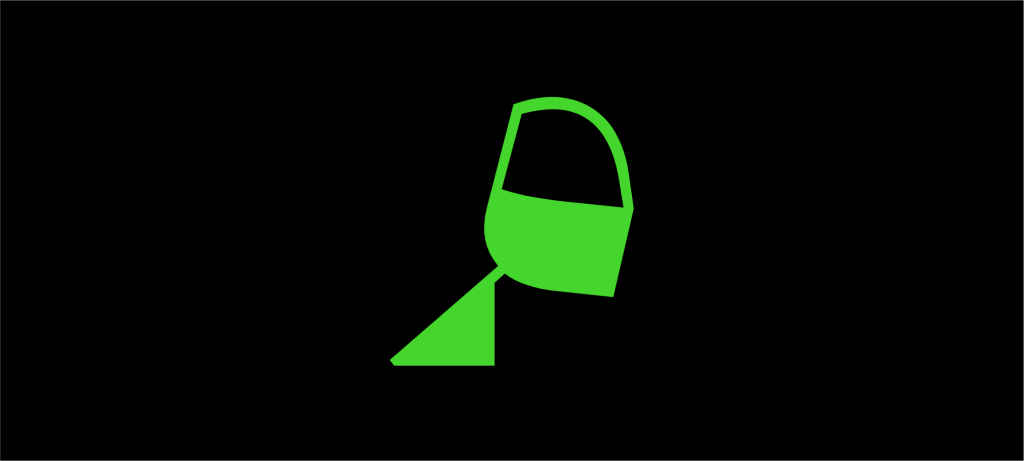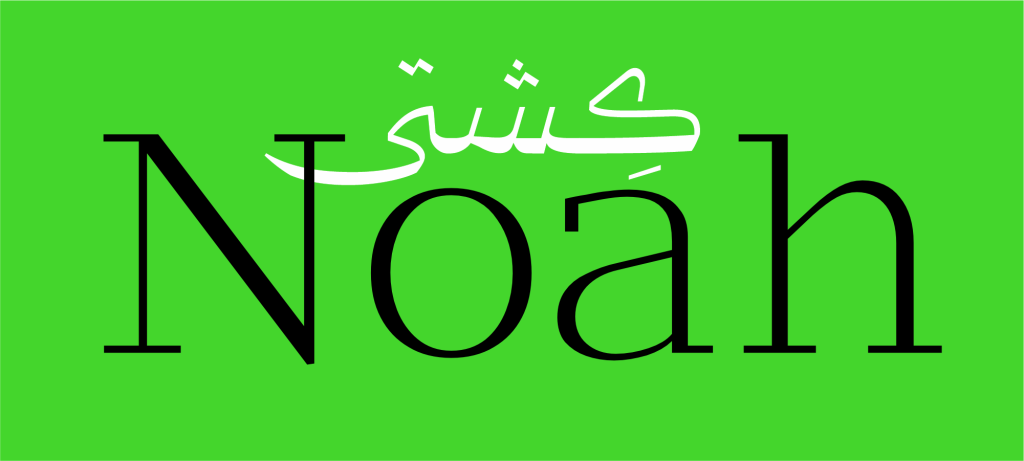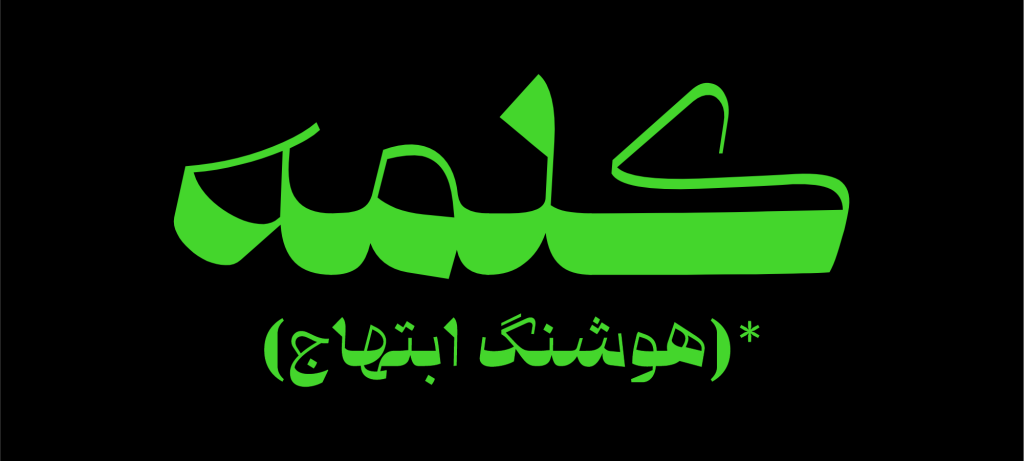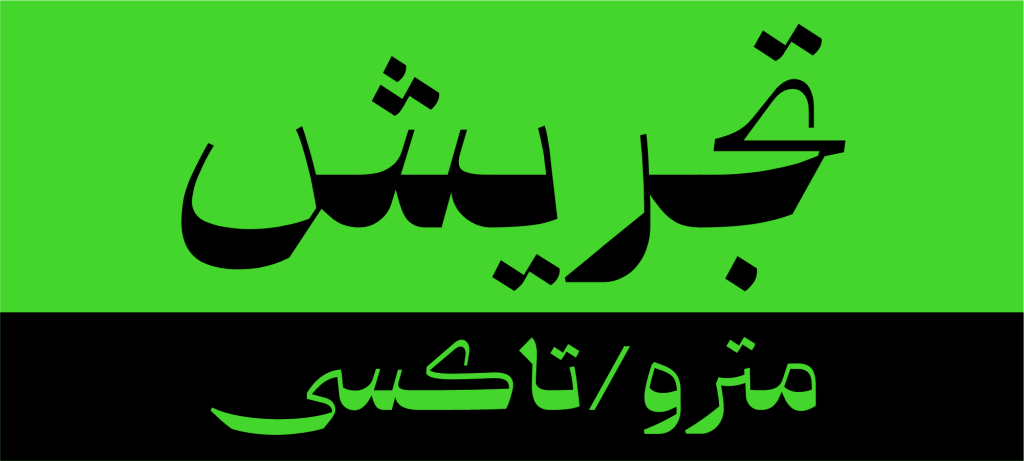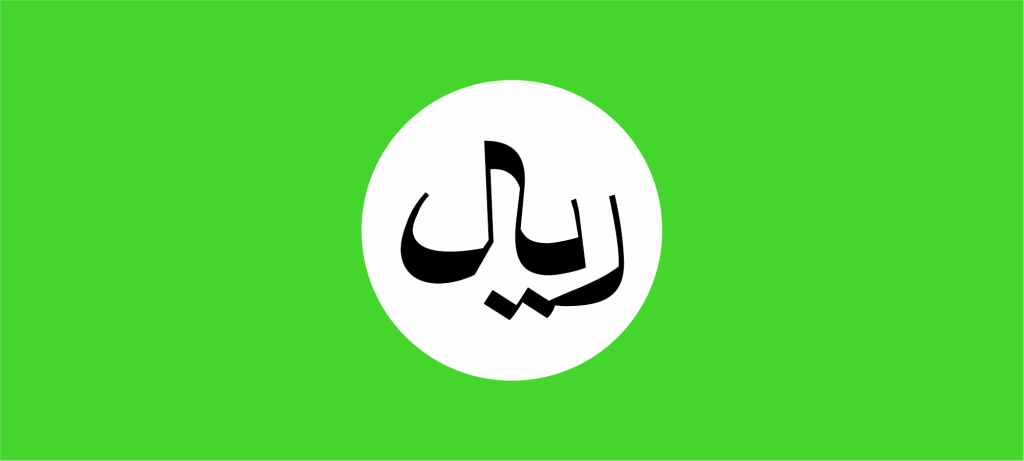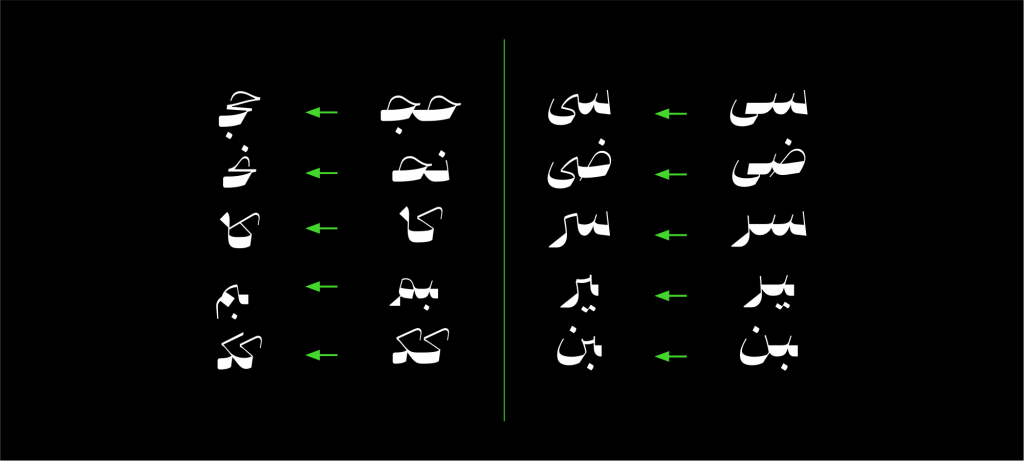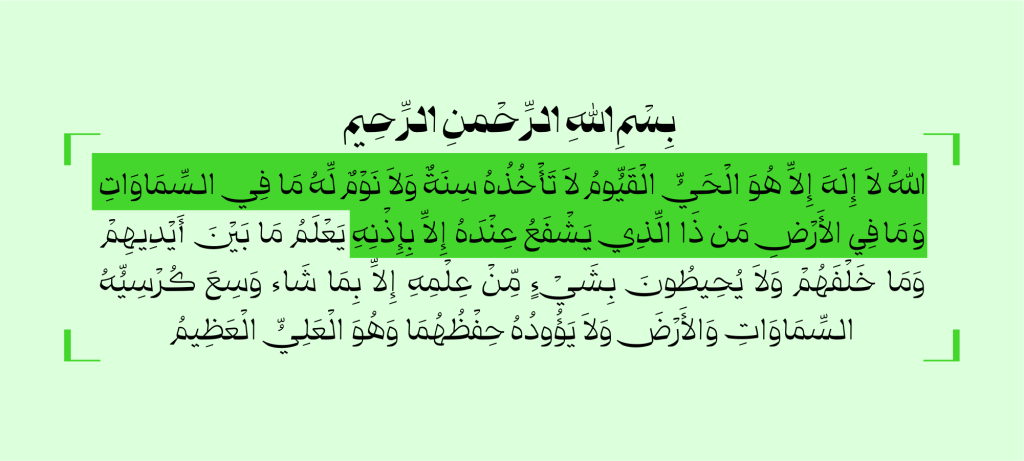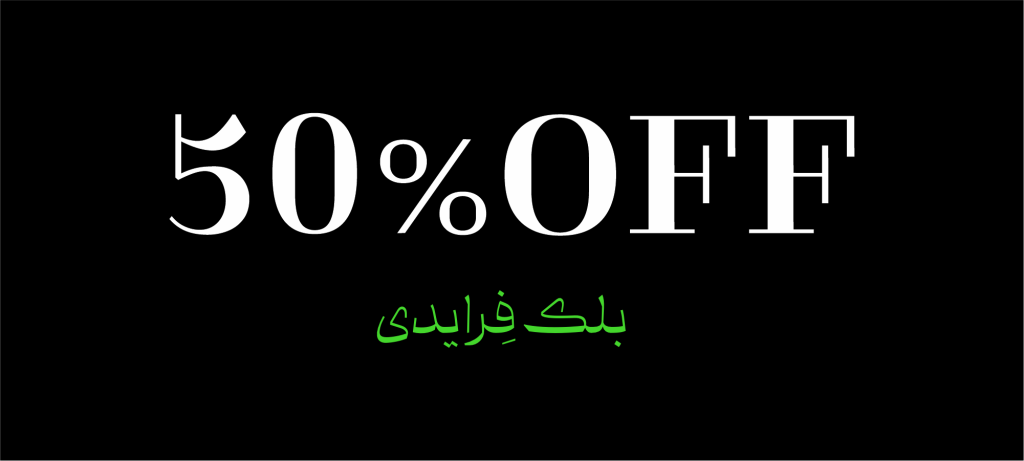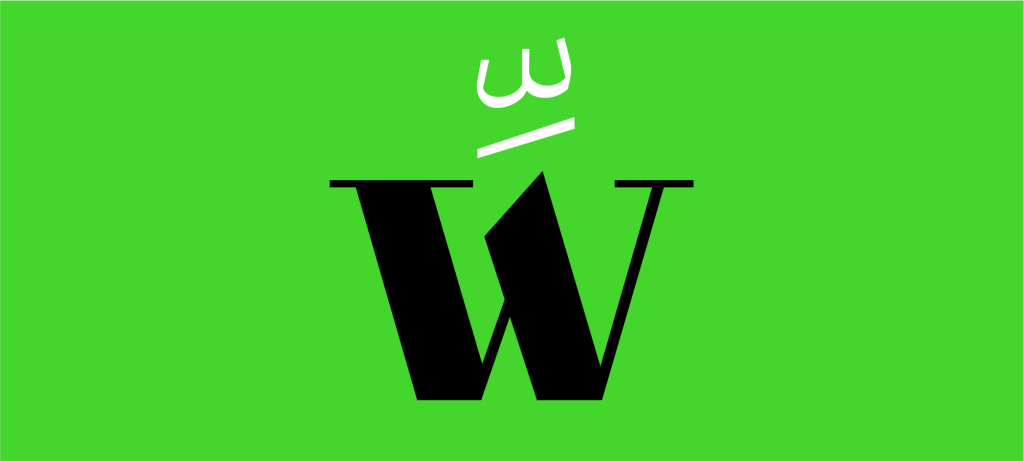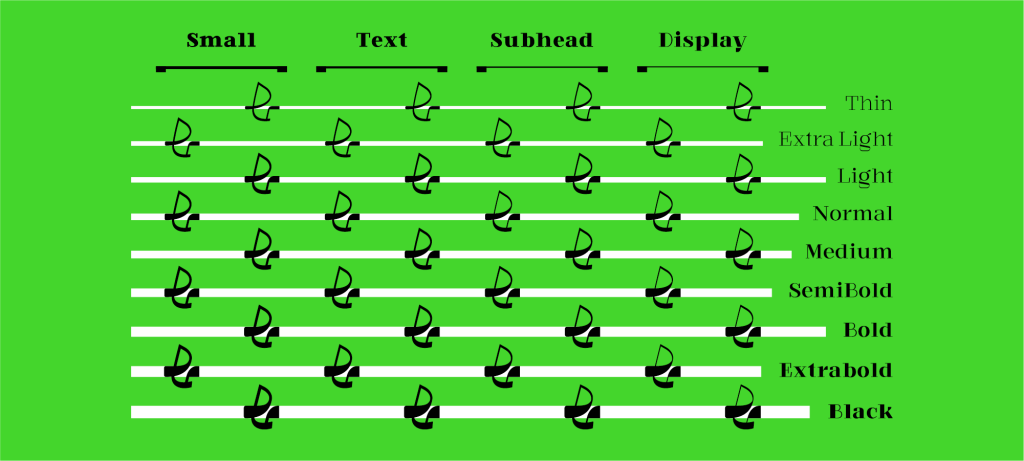
فونت قرنطینه قلمی مناسب برای متون کوتاه و عناوین خلاق نمایشی و تبلیغاتی است . قرنطینه با لحن بی باک خود به آسانی در هر نوع اثر تبلیغاتی خود را به رخ می‌کشد.
فونت قرنطینه قلمی با ویژگی نمایشی بالا
فونت قرنطینه، نتیجه تلاش 2 ساله محمدرضا چیت ساز طراح و دانش آموخته گرافیک از داشنگاه تهران است . این تایپ فیس از خانواده نسخ به شمار می رود و دارای ویژگی نمایشی بالایی است. به دلیل مذکور و فذم خاص طراحی گلیف ها و حروف این قلم مناسب برای متون کوتاه خلاق و عناوین نمایشی و تبلیغاتی می باشد.
قرنطینه تلفیق و ترکیبی از هندسه و خوشنویسی است. توجه و تمرکز به جزییات دقیق و منحصر به فرد در این تایپ فیس به ویژه در سایز‌های بزرگ و تیتر ها نمایان تر می‌شود.همچنین استایل Optical Size برای این قلم در نظر گرفته شده که کمک می‌کند، متناسب با سایز نوشته، مقدار کنتراست ضخامت را کنترل کنید.
با دقت در این تایپ فیس به طراحی خلاقانه و ابداع فرم‌های جدید و نوین در عین رعایت فرم و ساختار خانواده نسخ پی می بریم. که سبب خلق فرم های و گیلف های بسیار ویژه و ایده جدید شده است . تمرکز بر استفاده از سطح در مقایسه با دور و برجسته‌سازی شکستگی‌ها در برابر منحنی‌ها از مهمترین ویژگی های قرنطینه است.
از نقطه نظر ویژگی های مذکور و شباهت ظاهری فونت پیکان نزدیک و هم خانواده قرنطینه به شمار می رود. اگر به دنبال قلمی خاص با ویژگی نمایشی بالا جهت جذب نگاه خوانندگان هستید پیکان انتخابی از این جنس همانند قرنطینه می باشد.
پشتیبانی قرنطینه از حروف جایگزین (Discretionary Ligatures)
ترکیبات و حروف جایگزین یا همان Discretionary Ligatures مزیتی ویژه برای هر تایپ فیس و قلم به شمار می رود که سبب افزایش جاذبه بصری و همچنین ایجاد تنوع و خلق پویایی بیشتر در طراحی می گردد. قرنطینه با بهره مند بودن از این قابلیت دست طراحان را بازتر برای خلق نوآوری و دوری از یکنواختی می کند.
حروف کشیده ( Swash letters) در قرنطینه
در این تایپ فیس ویژگی حروف کشیده در خوشنویسی در فونت گنجانیده شده و برای کنترل طول خطوط و زیبایی متون مورد استفاده قرار می‌گیرد. استفاده از این قابلیت سفارشی و به سلیقه شما بستگی دارد.
پشتبانی از زبان های مختلف و تنوع اوزان گوناگون
خانواده فونت قرنطینه دارای 9 وزن و 4 استایل Optical Size  می‌باشد . این تنوع سایز و استایل ها امکان استفادهای گسترده ای را، از چاپ گرفته تا فضای مجازی پیش روی شما قرار میدهد. همچنین در قرنطینه حروف لاتین و زبان عربی هم همانند زبان فارسی به گونه ای طراحی شده اند تا همخوانی و هماهنگی را با زبان فارسی داشته باشند و همنشینی لازم را ایجاد کنند.
فارسی , انگلیسی , عربی
9 وزن، 4 سبک